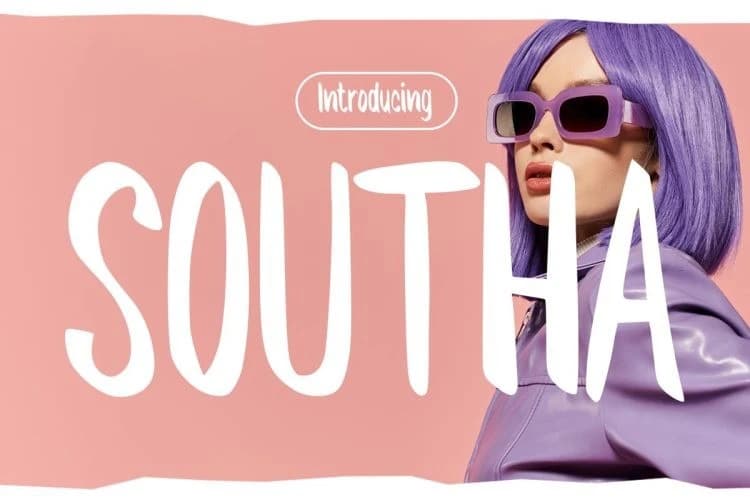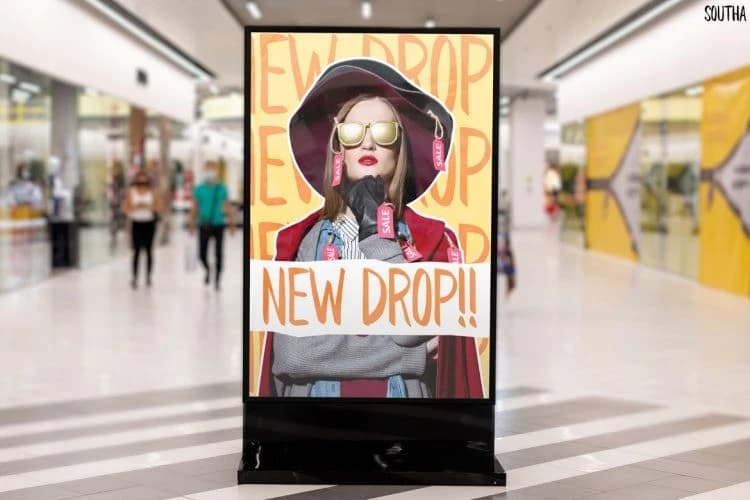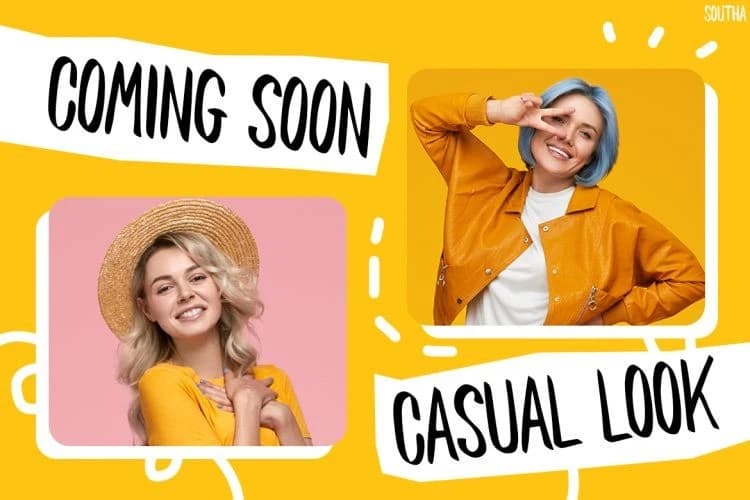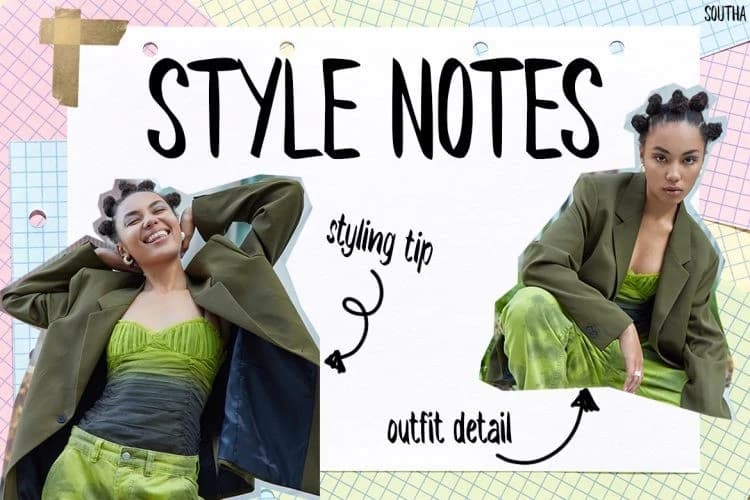
Southa Playful Font
Southa Playful Font, taze ve şık bir el yazısı hissi sunar ve görsellerinizi anında yükseltir. Ayrıca, uzun ve hafif düzensiz çizgileri otantik bir el yazısı görünümü yaratır; bu da her şeyi temiz ve okunabilir kalmasını sağlar.
Southa Playful Font, görsellerinizi anında yükselten taze ve şık bir el yazısı hissi sunar. Ayrıca uzun ve hafif düzensiz çizgileri, otantik bir el çizimi görünümü yaratır ve tüm öğeler temiz ve okunabilir kalır.